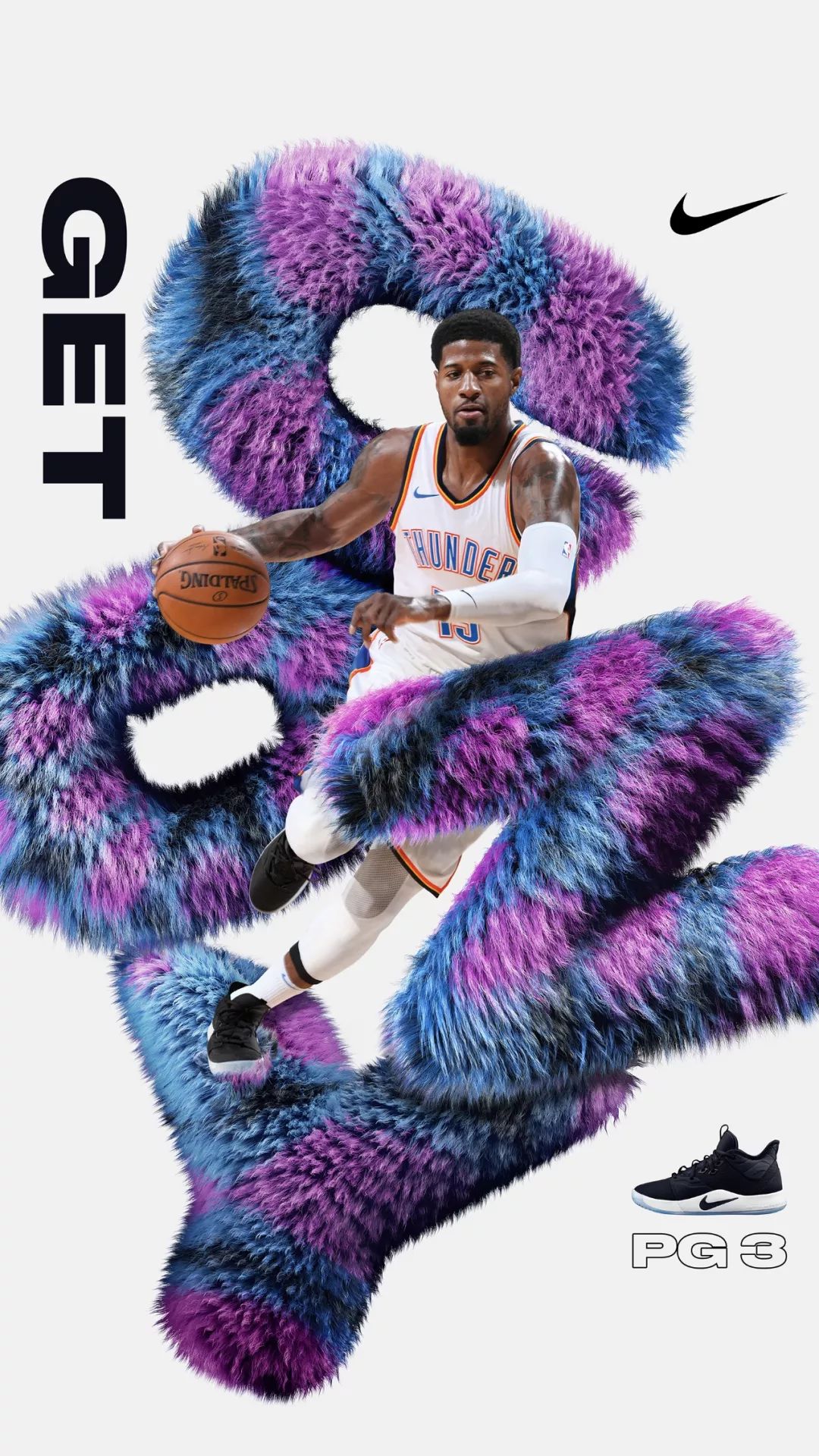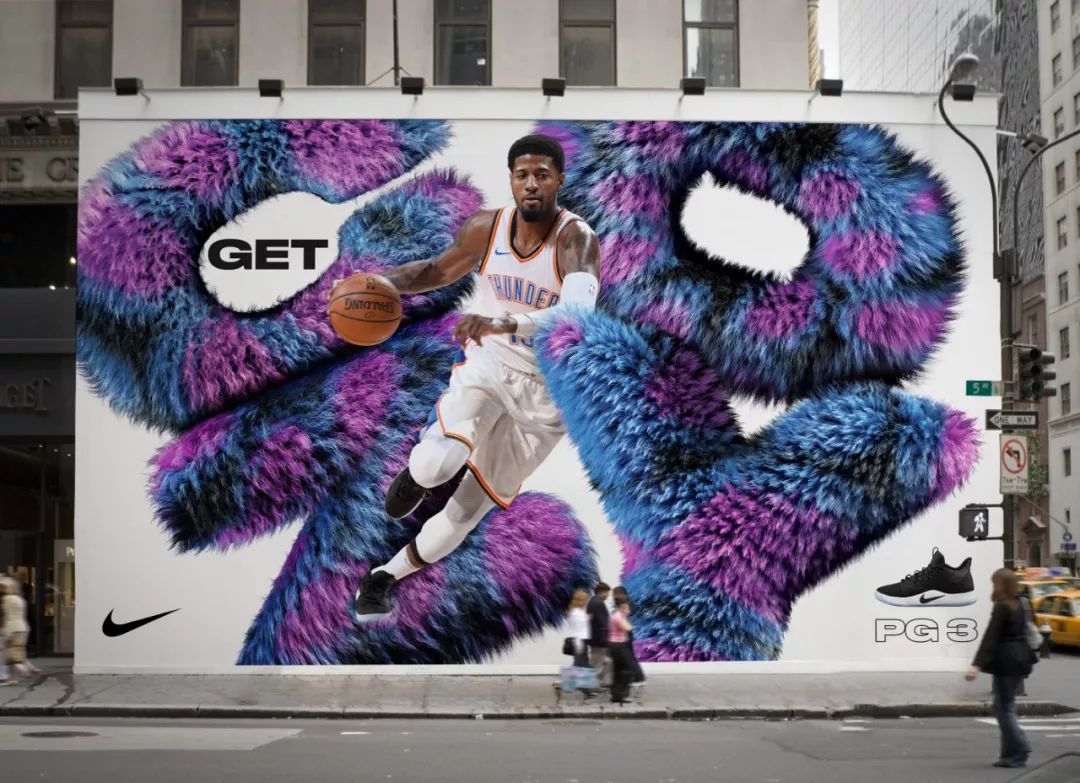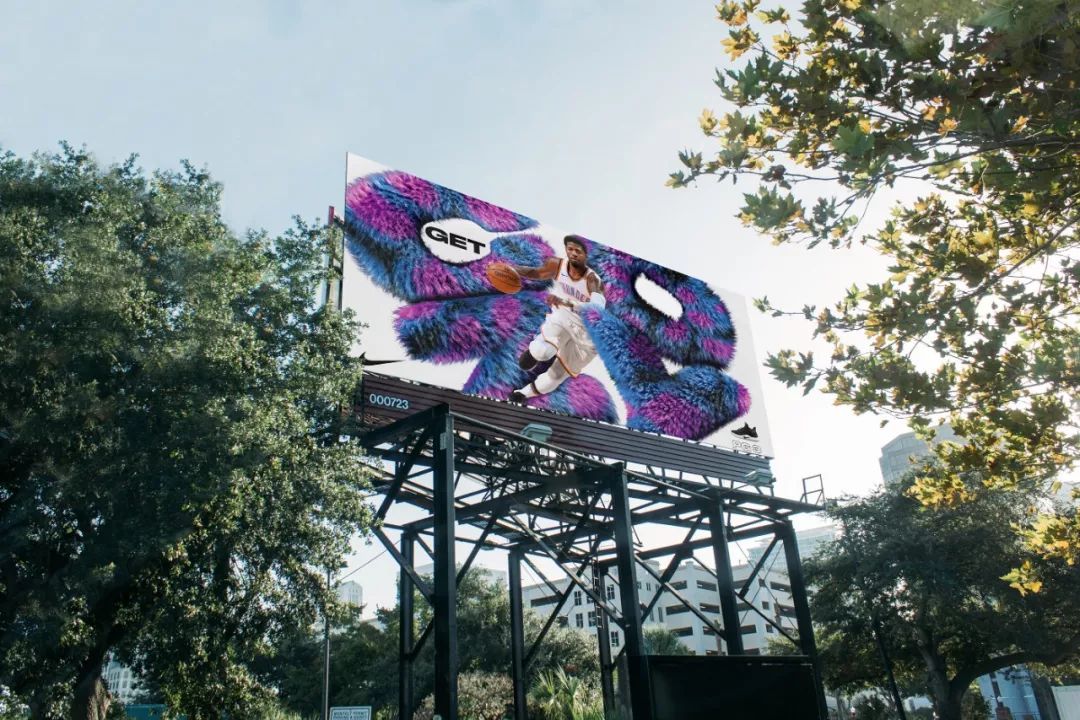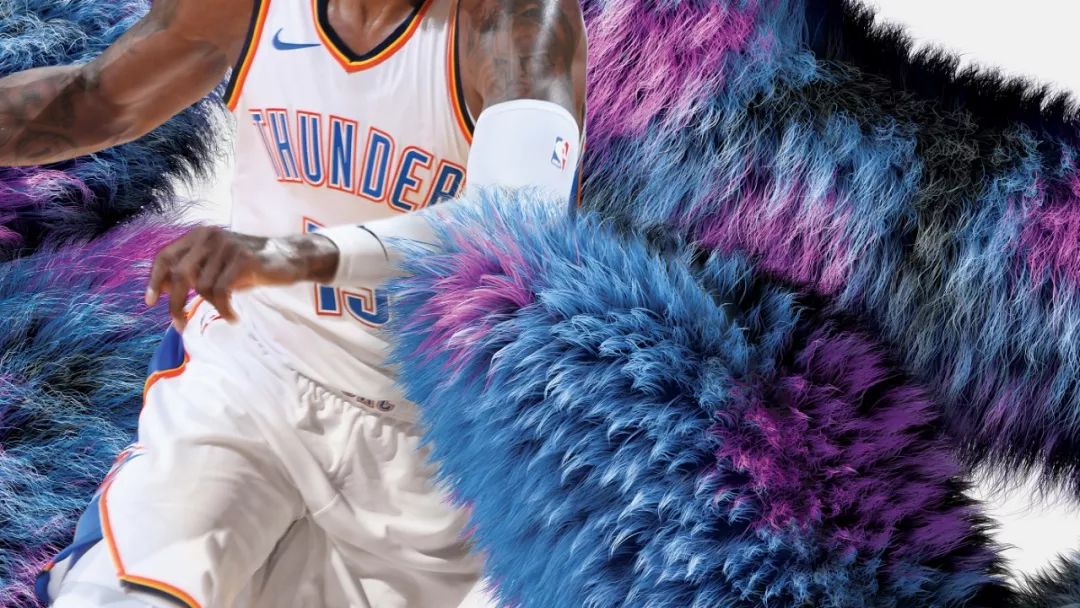
NIKE新广告设计太酷!毛茸茸的LOGO神似怪兽大学Sulley!
但除了在创意上遥遥领先,Nike更对设计品质有极高的要求,在他们全新一代Paul George's的鞋款的广告中,体现的淋漓尽致。
乍一看这个标志性logo,会让人联想到怪兽大学中的Sulley
这次Nike邀请了来自爱尔兰先居住纽约的设计师Shane Griffin操刀制作,平面设计部分由Nike设计师Jay Giraldo完成。
两位设计师在2月27日于behance上传这件名为 NIKE - PG3 "Get Cozy" 的作品立马吸引了许多人的关注,作品有若干运动和静态元素,如gif、排版动画、广告牌海报和模拟皮毛质感的logo组成。
gif部分也十分具有创造力,
户外广告牌设计,
设计细节,
设计过程,